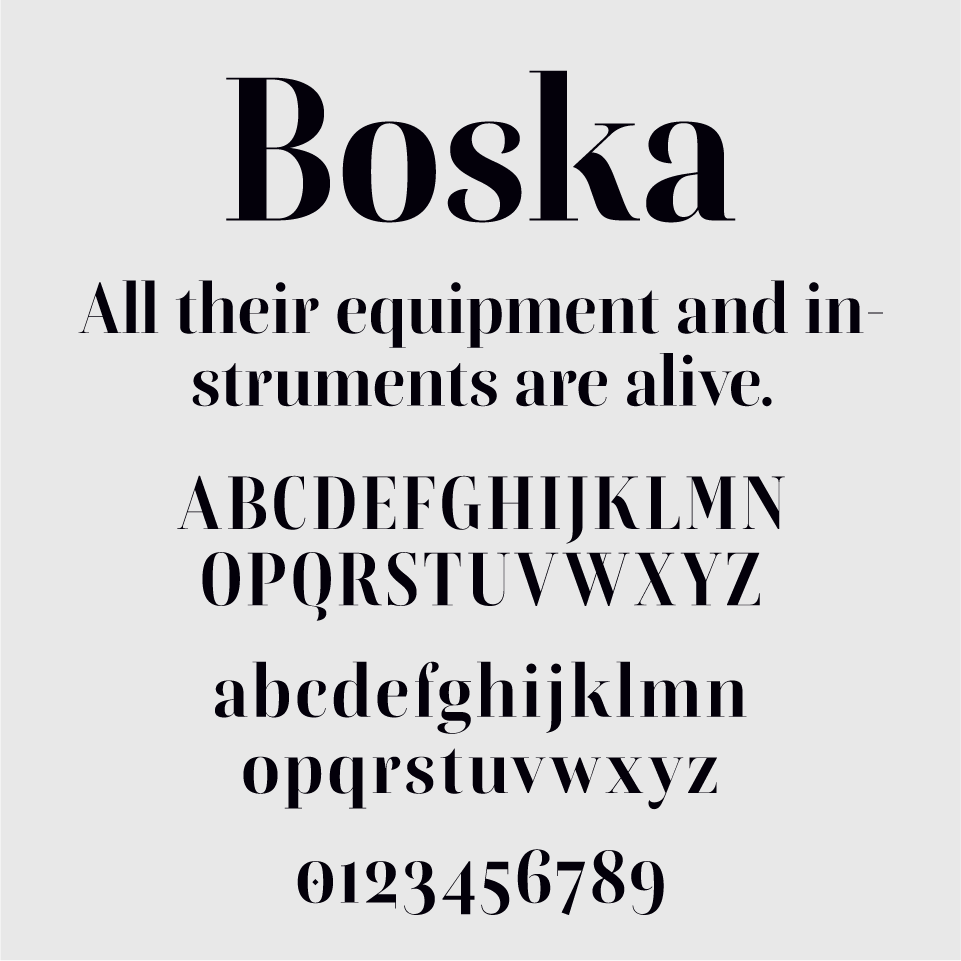
Boskaフォントは、シャープさと優雅さが共存するモダンクラシックなセリフ体フォントです。
セリフの大胆なコントラストと抑えたカーブが、ファッション誌のような洗練された世界観を思わせ、視線を惹きつけます。特に大文字の「B」や「K」に見られるエッジの効いたラインが印象的で、凛とした佇まいがあります。
一方で、小文字は角のとれた柔らかな印象があり、冷たすぎず、程よく感情を残したバランス感覚が光ります。クラシカルな要素を残しながらも、現代的なエディトリアルやアート系ブランドとの相性も良く、芯のある美しさが漂うフォントです。